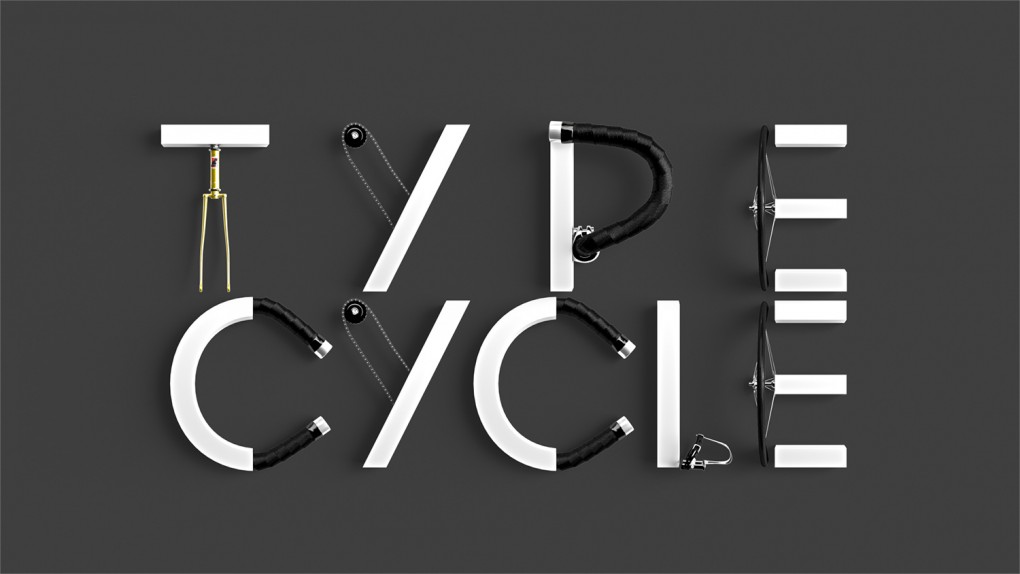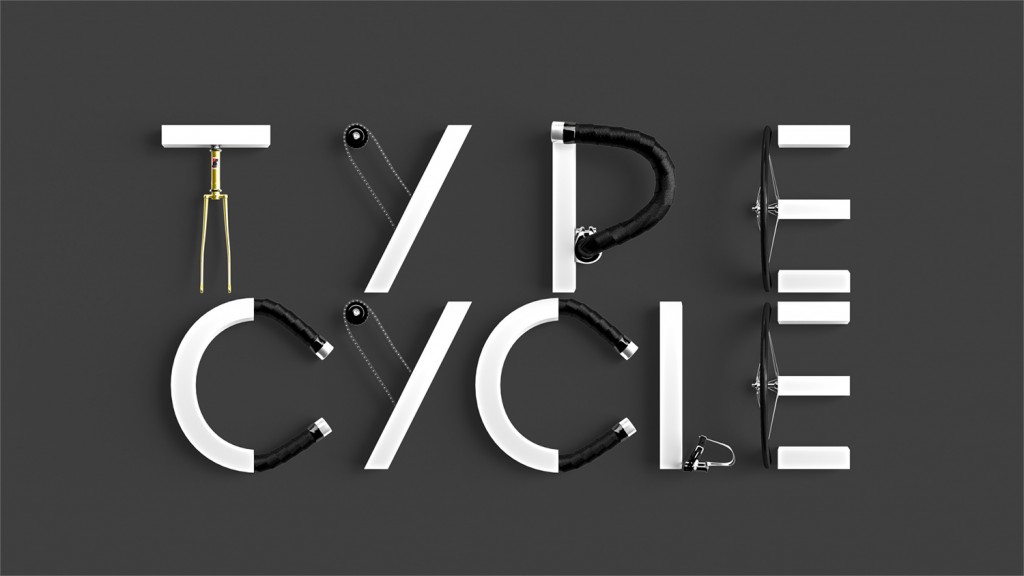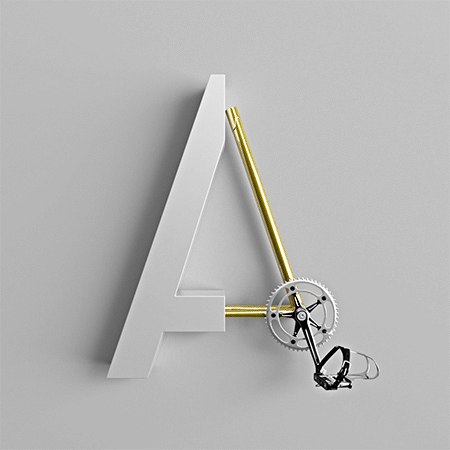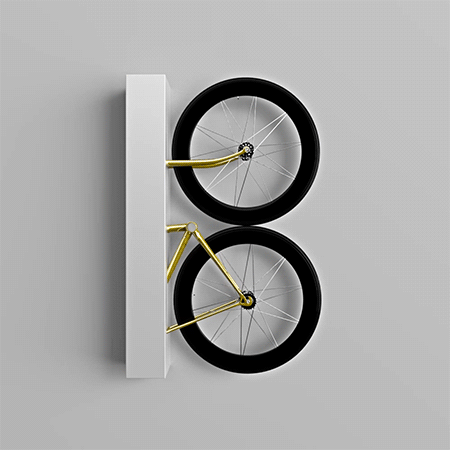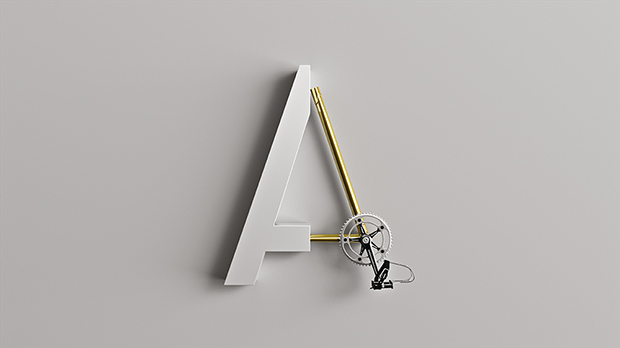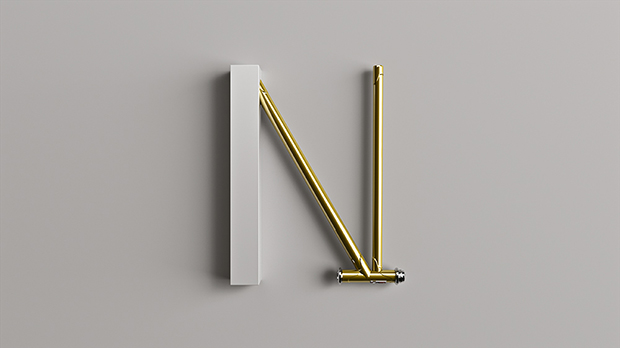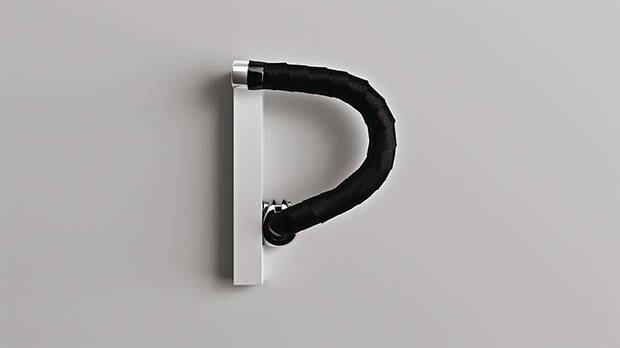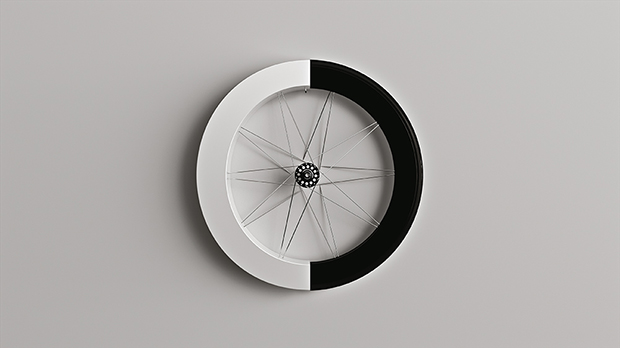
타입 사이클 : 자전거로 만든 글꼴
마르첼 피에카르스키가 만든 움직이는 글꼴은 자전거 ‘Bicycle’의 알파벳 ‘B’로부터 시작되었다. 런던의 모션 디자이너인 피에카르스키는 첫 번째 글자를 3D로 모델링 하는 동안 이 프로젝트를 확장하여 알파벳 전체를 완성하기로 마음먹었다. “3D 모델과 첫 글자 컨셉을 확정한 후, 저에게는 이 프로젝트를 확장하고 완성할 시간만이 필요했어요.”
피에카르스키는 시네마 4D, 애프터이펙트, 포토샵을 두루 활용하여 글꼴을 제작했는데, 알파벳 전체를 완성하는 데에 걸린 시간은 고작 3주였다. “회사 업무와 개인 생활을 병행하면서 시간을 내기는 어려워요. 이 작업에서 가장 많은 시간이 할애된 건 모델링이었죠.”
그가 말한다. “디자인을 마치고 나면 이 프로젝트의 애니메이션을 보고 싶다는 생각이 들어요. 아주 단순한 동작이라도 좋은 음향과 함께라면 근사해지거든요.”